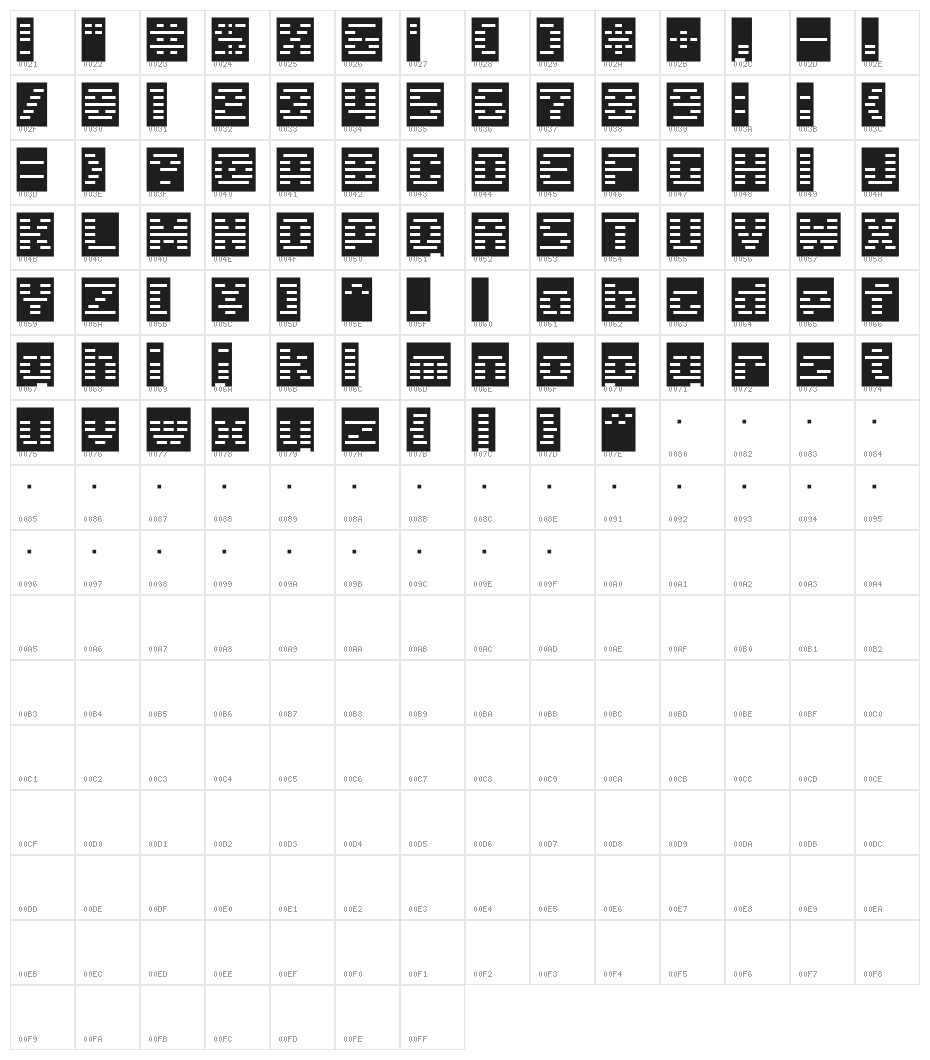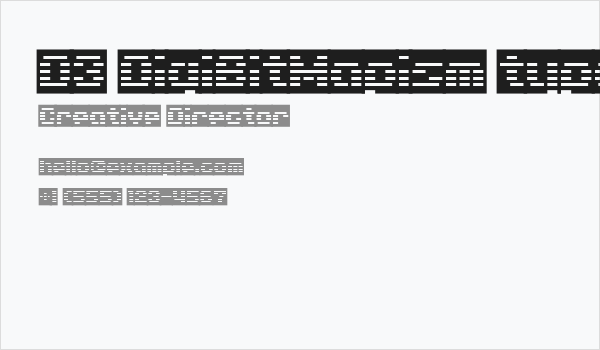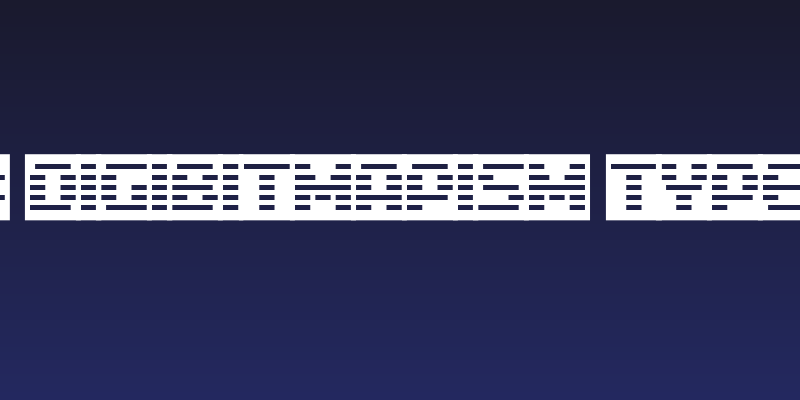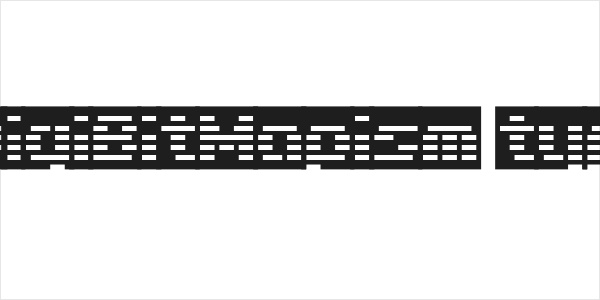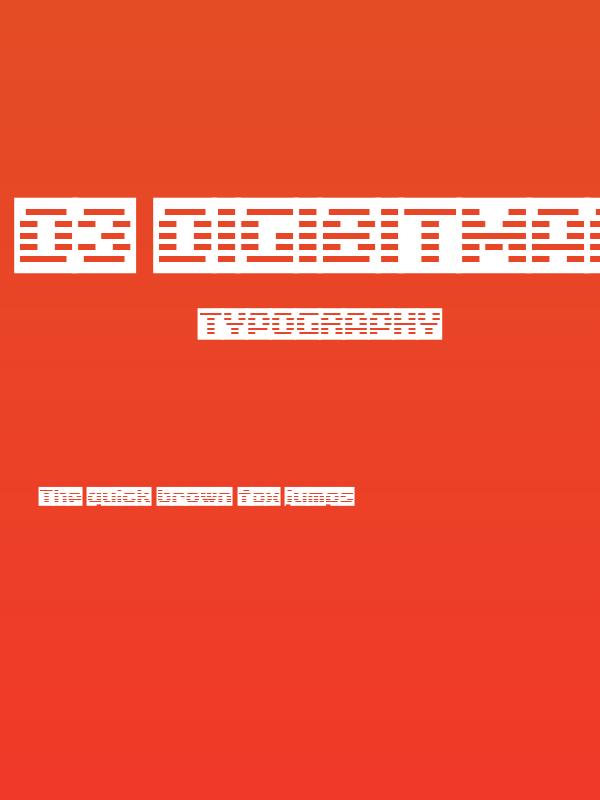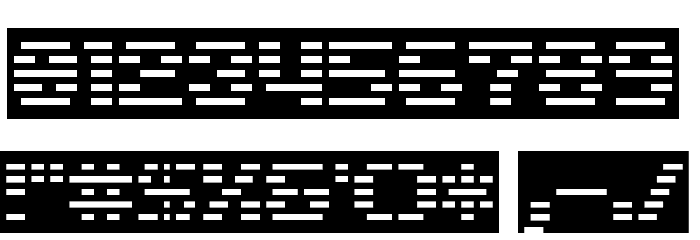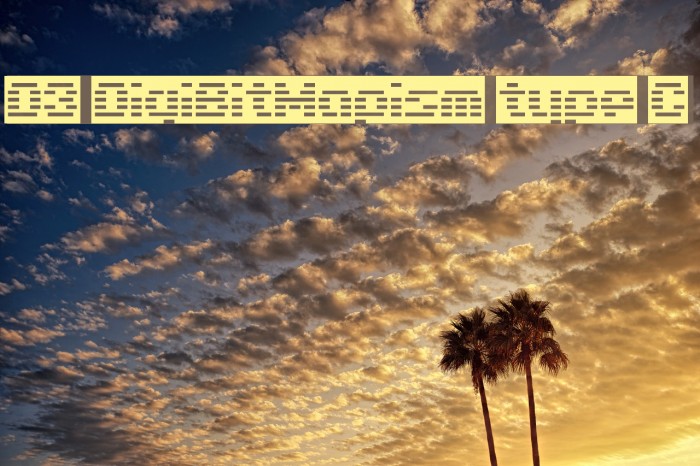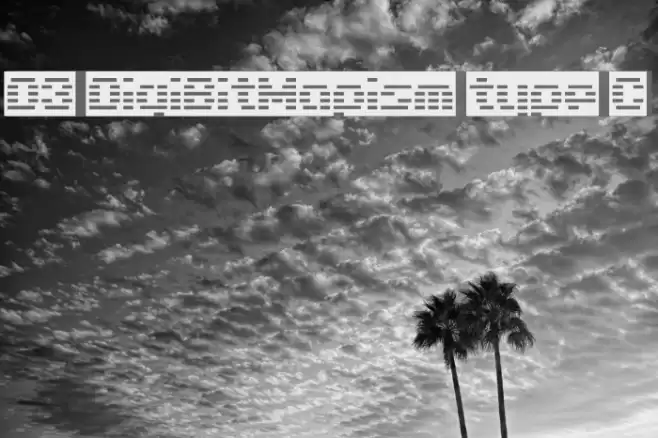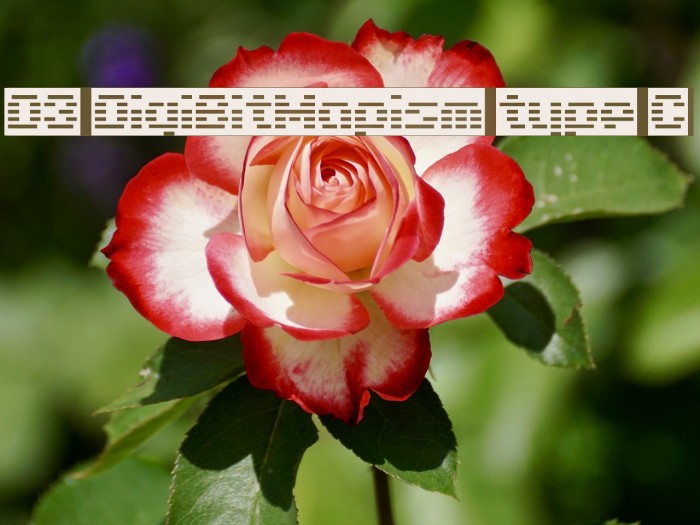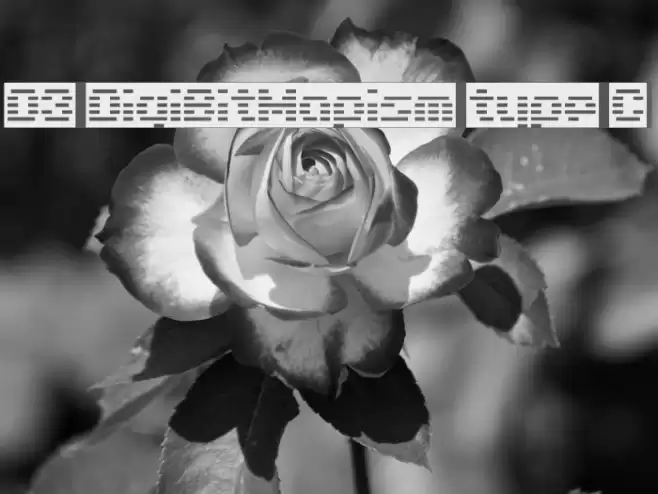
D3 DigiBitMapism type C Font
| Estilo general | Retro, Digital |
| Caso de uso | Logos, Headlines, Digital Art |
| Proyectos propuestos | Ideal for digital art, retro video game graphics, tech-themed posters, and any project requiring a vintage digital aesthetic. |